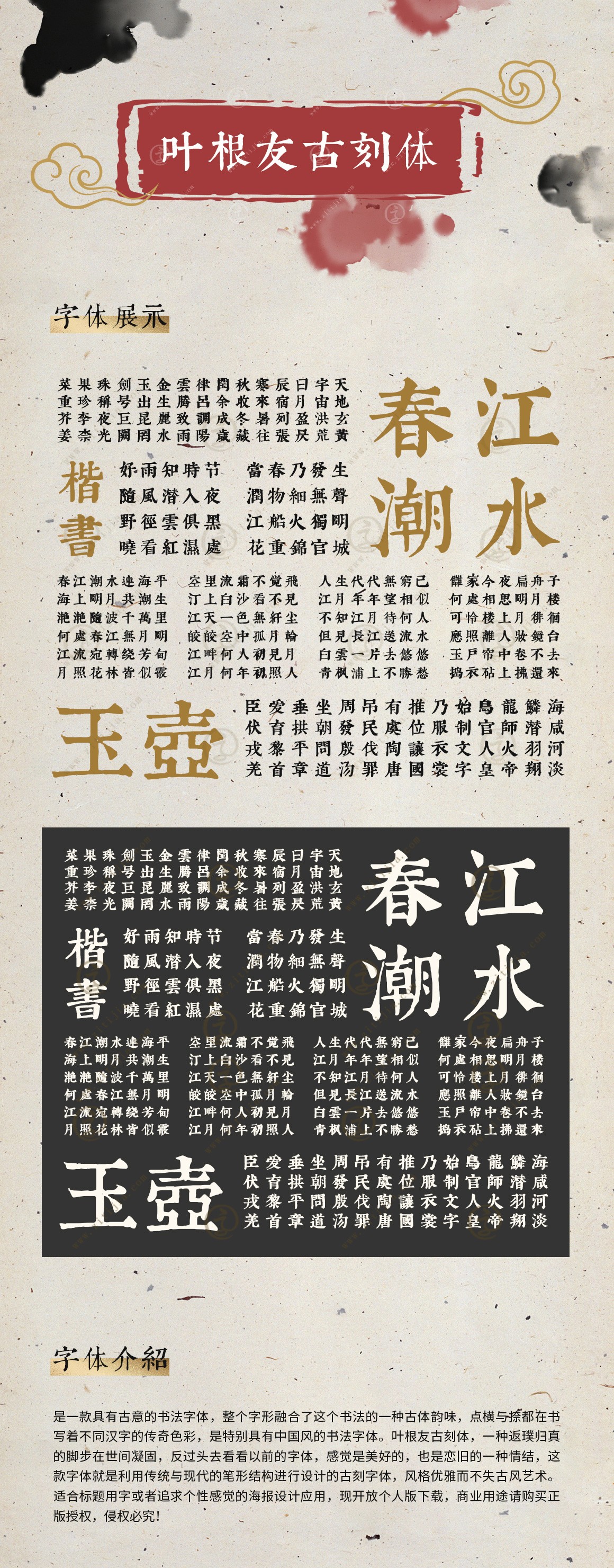
葉根友古刻體
字體作者:葉根友
創(chuàng)作年代:2016年
字體字數(shù):6763個中文漢字以及其他英文字母和阿拉伯數(shù)字
字體介紹
葉根友古刻體是一款具有古意的書法字體,整個字形融合了這個書法的一種古體韻味,點橫與捺都在書寫著不同漢字的傳奇色彩,是特別具有中國風的書法字體。葉根友古刻體,一種返璞歸真的腳步在世間凝固,反過頭去看看以前的字體,感覺是美好的,也是戀舊的一種情結(jié),這款字體就是利用傳統(tǒng)與現(xiàn)代的筆形結(jié)構(gòu)進行設計的古刻字體,風格優(yōu)雅而不失古風藝術(shù)。適合標題用字或者追求個性感覺的海報設計應用,現(xiàn)開放個人版下載,商業(yè)用途請購買正版授權(quán),侵權(quán)必究!